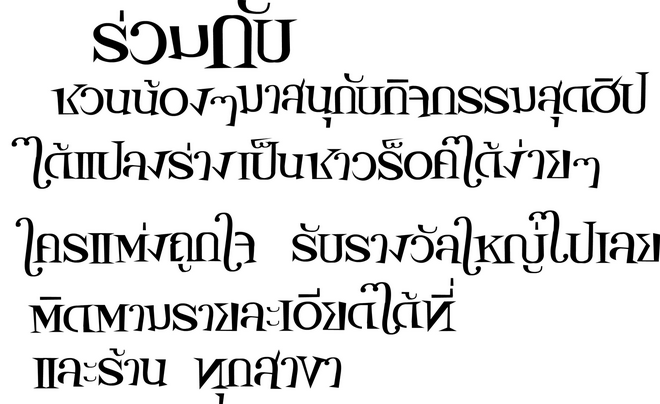
Allsmile เริ่มแรก
เป็นฟอนต์ประดับที่มีคุณภาพมากๆๆๆๆๆๆๆๆ
อันล่างนึกถึงฟอนต์ lumos ของ harry potter  :30:
ใช่ครับ แรง Balance ใจมาจากตัวนั้นล่ะ นี่ไง(ตรงคำว่า "เครื่องรางยมฑูต" ทีแรกจะว่าให้ชื่อ ยมฑูต แต่เกรงว่ามันจะน่ากลัวไปครับ)
กับของคนนี้ครับ
อันล่างนี่ใช่ของสามปะ ที่ทำเลียนแบบฟอนต์ hp สวยน่อร็อว์กอะ!  :25:
คงใช่ครับ ผมไม่ได้ติดตาม เพิ่งสมัครเข้ามาเป็นสาวกเว็บนี้ครับ แต่เห็นแล้วออกแนวดีครับ
เลย Save มาดูครับ